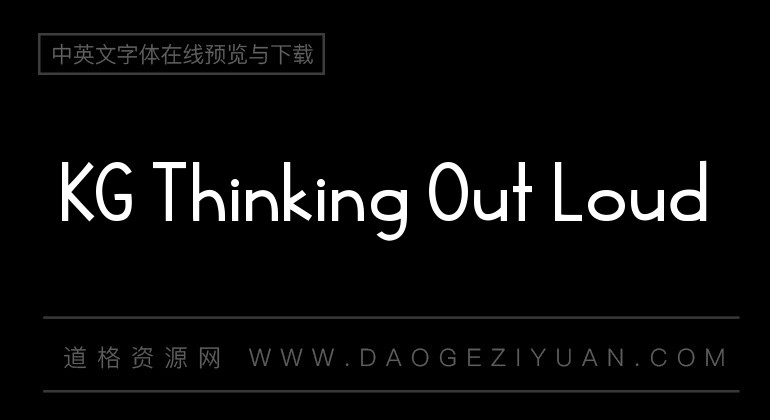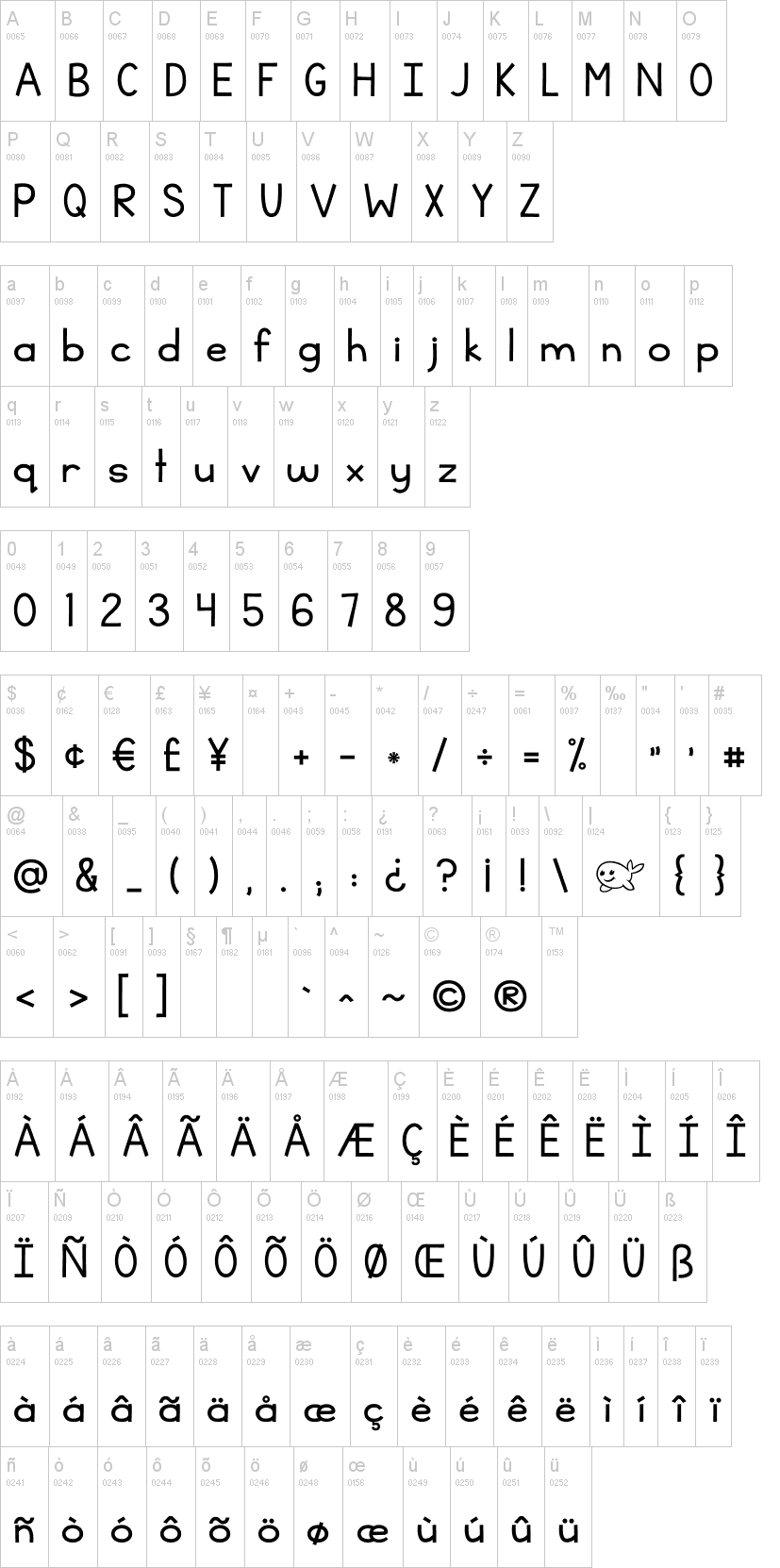
KG Thinking Out Loud是一款由英国设计师Katie Guthrie设计的手写字体。它是一种温暖、简约、可爱的字体,可以用于婚礼、海报、卡片等任何类型的设计。KG Thinking Out Loud字体的特点是,它有着自然的流畅线条,它的字母格式比较大,比较粗糙,可以更好地表达出设计师想要表达的情感。它也有着更多的变形,可以自由组合,使设计更加有趣。内容介绍
KG Thinking Out Loud是一款非常不错的手写艺术字体,具有很好的视觉感,适合于文化类的宣传设计、商业类品牌的广告和产品包装设计以及个性化文字排版等较多场景。